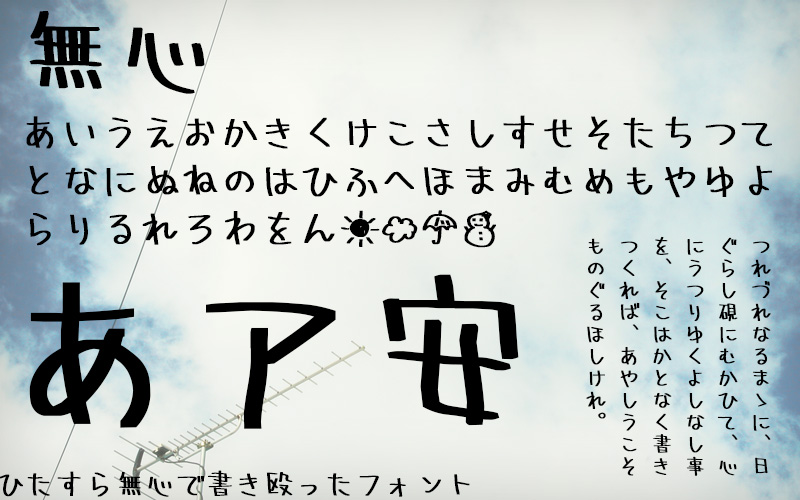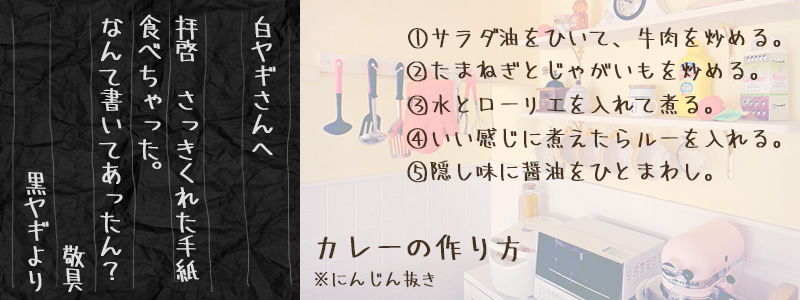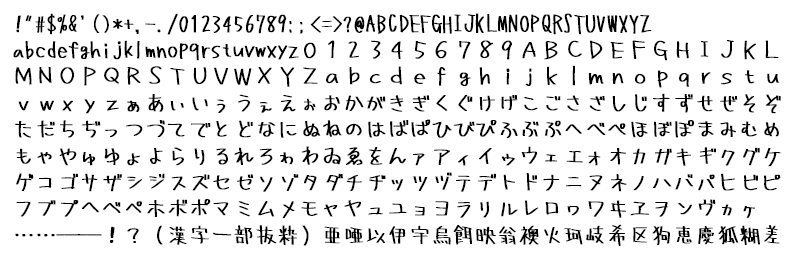
无心手写体字体信息
只是我天真烂漫的手写字体而已。
这只是作者的性格,没有主题或概念。
它很脆,所以最好用小一点的。
- Adobe-Japan1-3 标准
- 平假名、片假名、一级和二级汉字、IBM 扩展汉字等。
- 我没有制作盒装字符(┸┼像这样),因为我无法手动连接它们。其他特殊符号(那些在日常写作中很少使用的符号)到处都不见了。当我喜欢的时候,我会做到的。
- 由于它比虚拟身体小,如果按原样组装,它往往会变得松软。我们建议适当调整字符。